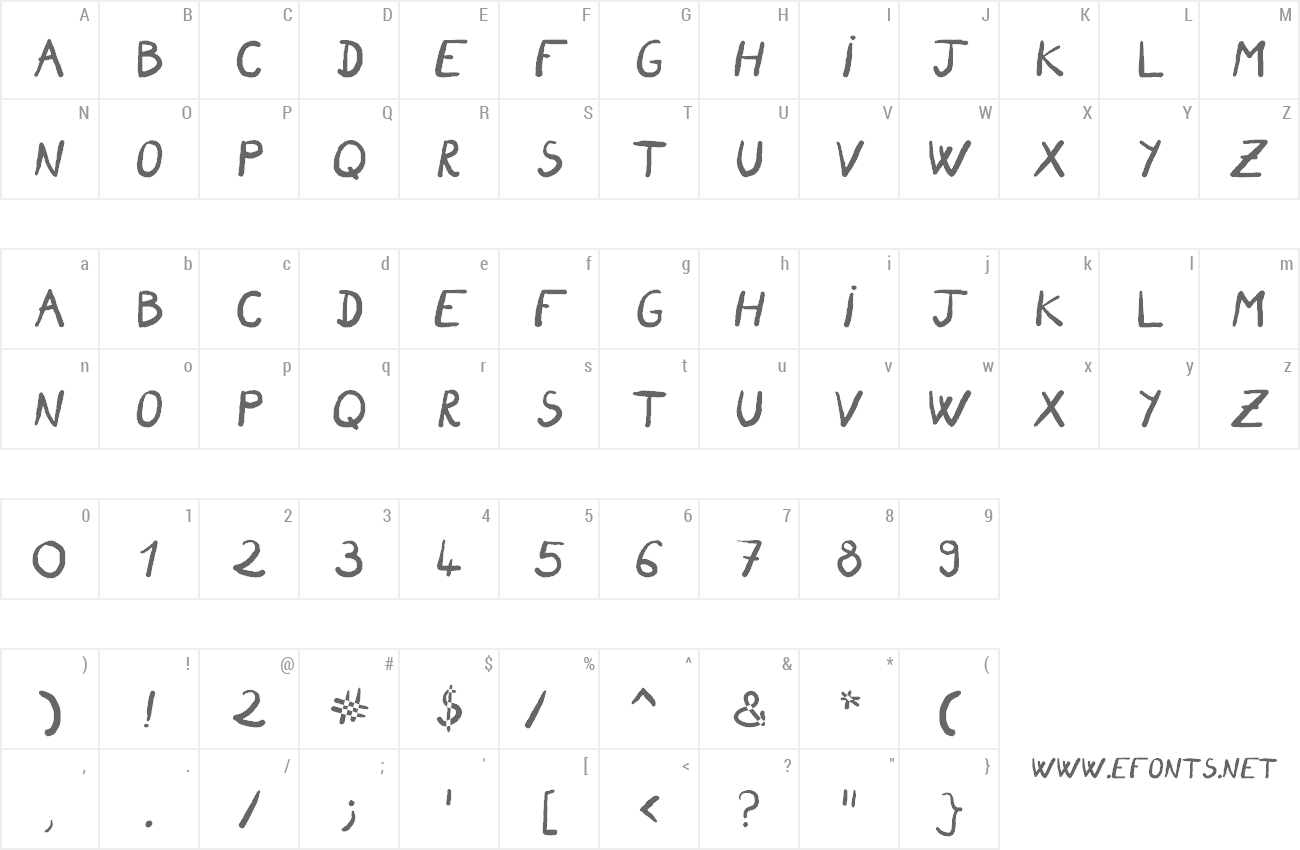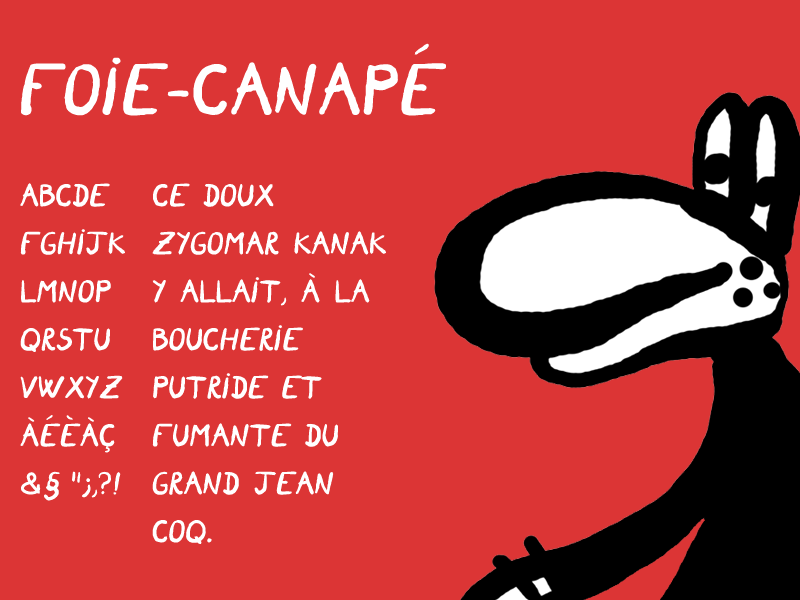
Preview and download Foie Canape Font. Created by Joël Frl in Fancy Comic styles with 100% Free license.
Voici la version complète et gratuite de cette police de caractère, "Foie Canapé". Elle est dessinée à la base pour le lettrage en Bande Dessinée. |